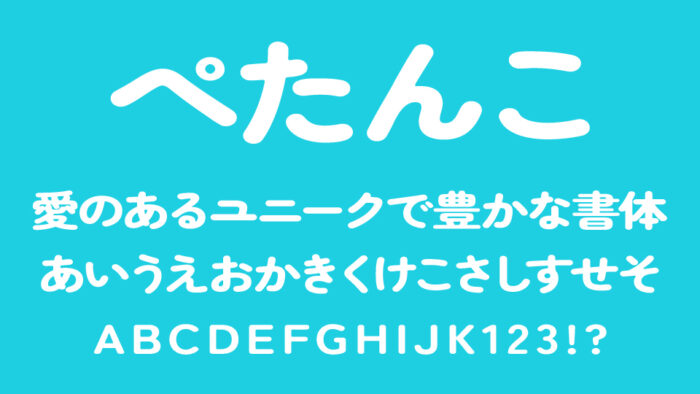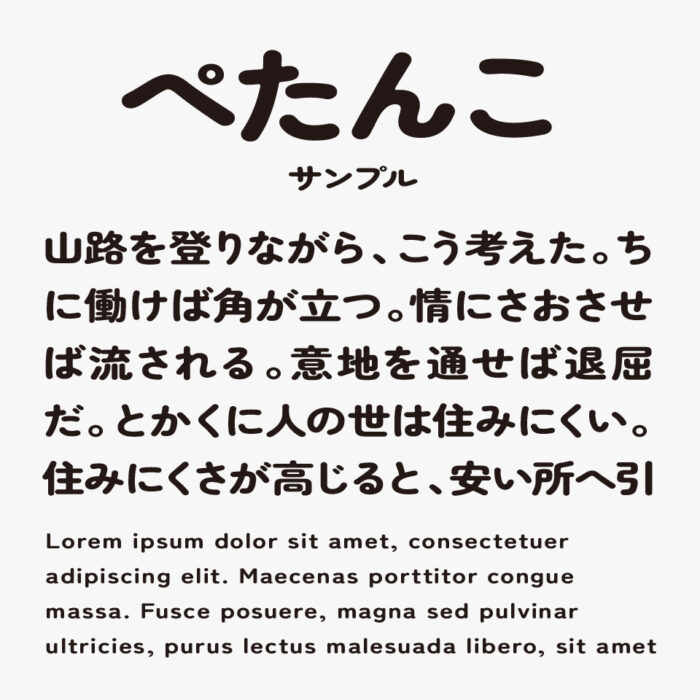
ぺたんこ
ぺたんこフォントは、Zen丸ゴシックフォントをベースとして、横長に変形し手描きっぽい揺らぎと丸みを加えた角丸ゴシックフォントです。
丸みと素朴さを活かしたちょっと平たいシルエットがとても可愛いくて、ポップさと落ち着きのバランスが取れたフォントに仕上がっています。
ウェイトも3種類用意されているので、用途にあわせて使い分けることができるのも嬉しいです。